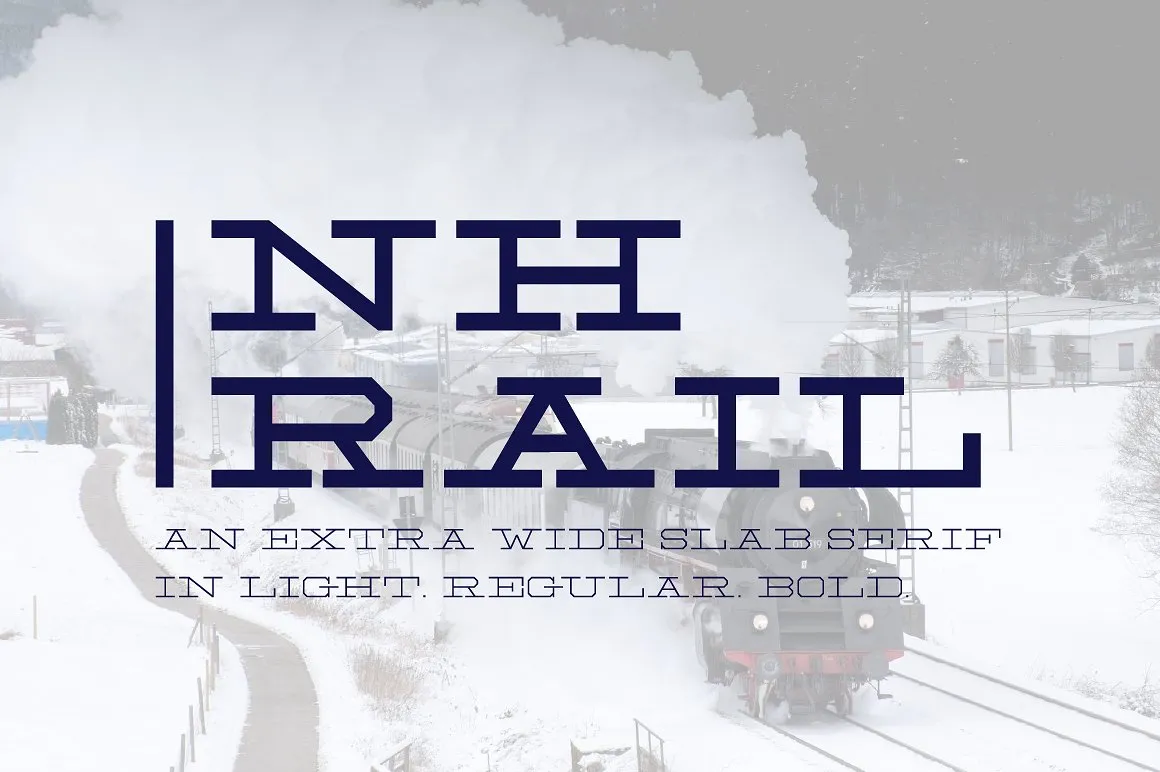
Aqui está uma descrição em português para a página de download da font ‘NH Rail Slab Typeface’, seguindo as instruções fornecidas: Introduzimos NH Rail Font, criado pela Von Type Co., uma fonte premium disponível na CreativeMarket. Agora é o momento ideal para experimentar sua liberdade gratuita! Inspirada no logo antigo da New Haven Railroad (1872-1968), este tipo de tipo exibe um estilo em letra quadrada inspirado nos serifs largos e robustos do início do século XX, combinados com um design moderno e blocoso. Isso criou uma aparência impactante que complementa qualquer projeto de desenho ou logotipo. NH Rail Slab Typeface oferece uma variedade de pesos e estilos para combinar com a vastidão de projetos onde a eficácia é fundamental. Este tipo de tipo traz um sabor único à sua identidade visual, iluminando seu design e garantindo que sua marca seja reconhecida claramente em qualquer plataforma digital ou impressa.